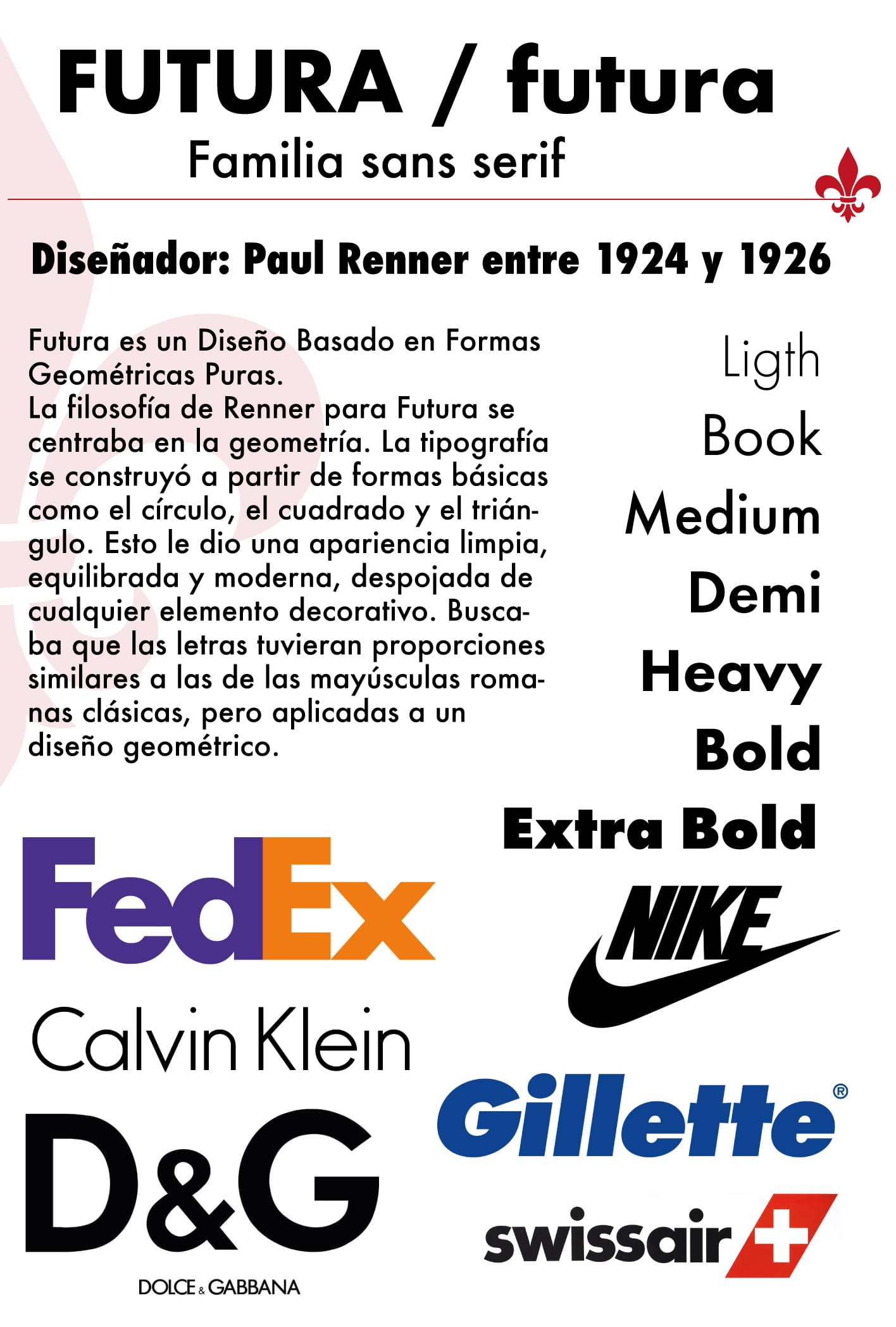
Futura, la tipografía moderna
Esta tipografía Futura fue realizada por Paul Renner en 1927 para la casa Fundición Tipo Bauer.
Futura es, sin lugar a dudas, una de las fuentes más influyentes y reconocibles del siglo XX.
Futura fue realizada por el tipógrafo Alemán Paul Renner (1887-1956), comienza su creación durante 1924, la concluye a principios del año 1927, fue un encargo de la casa Fundición Tipo Bauer.
Futura surge de la corriente Bauhaus y del movimiento moderno, que buscaban la funcionalidad, la simplicidad y la geometría en el diseño. Renner se propuso crear una tipografía que representara el espíritu de la nueva era industrial, libre de ornamentos y basada en formas geométricas puras como círculos, cuadrados y triángulos. Esto la convierte en un ejemplo clásico de una tipografía sans-serif geométrica.